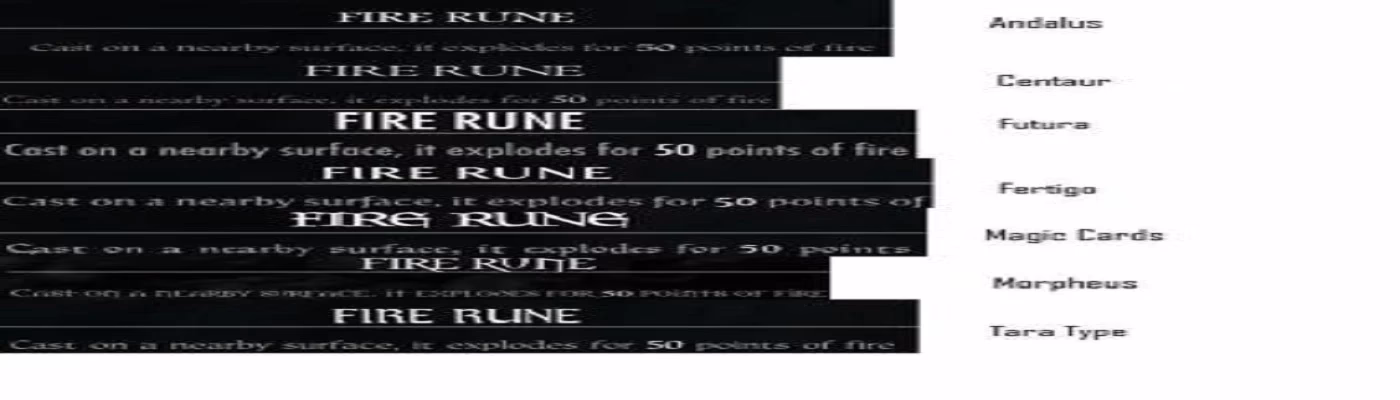
Cuando un juego tiene una comunidad tan activa y creativa como la de Skyrim, es de esperar que cada pequeño rincón del juego sea susceptible de ser modificado y personalizado. Desde armaduras y armas hasta sistemas de magia completamente nuevos, las posibilidades son casi infinitas. Sin embargo, a menudo pasamos por alto uno de los detalles más presentes y constantes en nuestra pantalla: la tipografía. Aunque parezca un cambio menor, modificar las fuentes del juego puede tener un impacto sorprendente en la atmósfera y la jugabilidad, renovando por completo la experiencia de juego y haciendo que un título con más de una década a sus espaldas se sienta fresco y diferente. Si quieres darle un lavado de cara a tu interfaz, aquí te presentamos los mejores mods de fuentes para Skyrim.
Skyrim Interface Makeover: El Compañero Indispensable
Antes de sumergirnos en los mods que cambian directamente la tipografía, es crucial hablar de una herramienta que prepara el terreno. Cambiar las fuentes es genial, pero si la nueva letra es más ancha o más alta que la original, te encontrarás con textos que se cortan, menús desalineados y una interfaz caótica. Aquí es donde entra en juego Skyrim Interface Makeover.
Este mod no cambia la fuente por sí mismo, sino que ajusta de manera inteligente los elementos de la interfaz de usuario (UI) para acomodar tipografías de mayor tamaño. Cajas de diálogo, descripciones de objetos, menús de habilidades... todo se expande y se reorganiza para que cualquier fuente que instales se vea perfecta. Además, incluye opciones de personalización adicionales para la interfaz, convirtiéndolo en una descarga casi obligatoria incluso si no planeas instalar un mod de fuentes de inmediato. Es la base perfecta para asegurar que tu personalización sea funcional y estéticamente agradable.
"¡Muchacho!". Si esa palabra resuena en tu cabeza, este mod es para ti. Skyrim y God of War (2018) comparten una profunda inspiración en la mitología y la estética nórdica. ¿Qué mejor manera de unificar esa sensación épica que llevando la tipografía de un juego al otro? El mod God of War 2018 Font Replacement hace exactamente eso, reemplazando la fuente de Skyrim por la icónica "Berzerker" utilizada en la aventura de Kratos y Atreus.
El resultado es una interfaz con un aspecto mucho más rudo, antiguo y poderoso. Cada texto, desde el nombre de una poción hasta el diálogo de un PNJ, adquiere un peso que encaja a la perfección con la ambientación de un Sangre de Dragón destinado a salvar el mundo. No estarás luchando contra los dioses Aesir, pero tu misión no es menos importante, ¡y merece una tipografía que esté a la altura!
Alternate Book Fonts: Para los Amantes del Lore
Uno de los mayores tesoros de Skyrim es su vasto y detallado lore, contado a través de cientos de libros esparcidos por todo el mundo. Sin embargo, seamos honestos: la fuente original de los libros no es la más cómoda para leer durante largos periodos. Puede resultar cansada para la vista y un poco monótona. Si eres de los que, como yo, disfruta devorando cada tomo que encuentra, Alternate Book Fonts es una bendición.
Este mod reemplaza la tipografía de los libros por una nueva, mucho más clara, elegante y agradable a la vista. La lectura se vuelve una experiencia más fluida y cómoda, invitándote a sumergirte de verdad en las historias de Tamriel sin forzar la vista. Con este mod, ya no tendrás excusa para no leer "La Doncella Argoniana Ardiente". Una mejora de calidad de vida que realza la inmersión en el mundo del juego.
Sovngarde - A Font Replacer: Fiel al Espíritu del Juego
¿Sabías que un mod de fuentes puede ser lore-friendly? La dedicación de la comunidad de modding de Skyrim no conoce límites, y Sovngarde es la prueba de ello. Este mod no utiliza una fuente preexistente de otro universo, sino que introduce una tipografía completamente nueva, creada desde cero con el único propósito de encajar en el mundo de Skyrim.
La fuente de Sovngarde tiene un diseño que evoca las antiguas runas nórdicas sin sacrificar la legibilidad. Es elegante, temática y se siente como si siempre hubiera debido estar en el juego. Además, uno de sus puntos fuertes es su amplio soporte para múltiples idiomas, incluyendo español, francés, alemán e italiano, asegurando que jugadores de todo el mundo puedan disfrutar de una experiencia coherente y atmosférica.
Tabla Comparativa de Mods de Fuentes
Para ayudarte a decidir, aquí tienes una tabla que resume las características principales de cada mod mencionado:
| Mod | Tipo de Fuente | Lore-Friendly? | Ideal Para... |
|---|---|---|---|
| Skyrim Interface Makeover | No aplica (Mod de UI) | Sí | Usuarios que quieren instalar cualquier mod de fuente sin problemas de compatibilidad. |
| God of War 2018 Font | Épica y Nórdica ("Berzerker") | Temáticamente sí | Fans de God of War y quienes buscan una estética más agresiva y legendaria. |
| Alternate Book Fonts | Clara y legible para libros | Sí | Jugadores que disfrutan leyendo todos los libros del juego y buscan comodidad. |